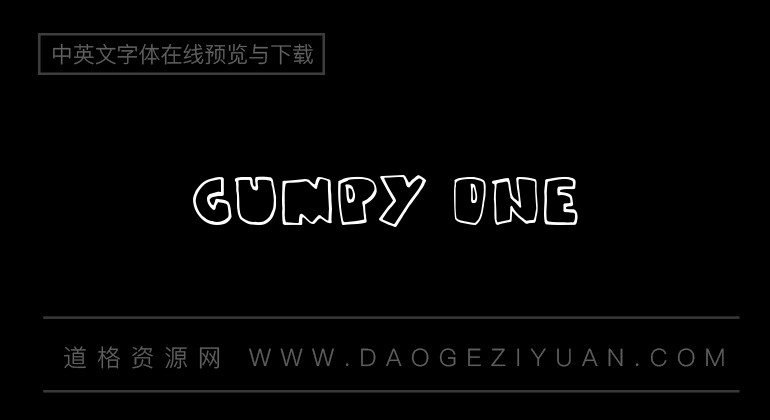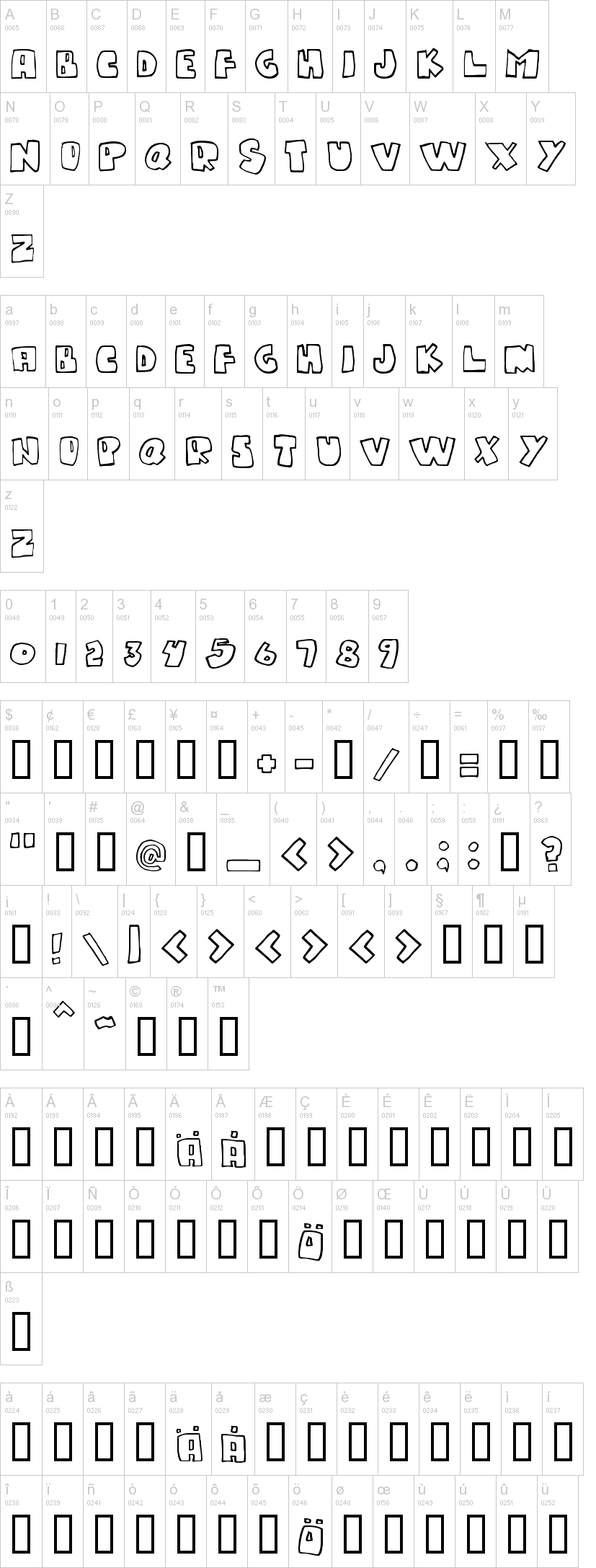
Gumpy One 是一款拥有独特风格的字体,由著名的设计师 Gumpymeme 创作。这款字体融合了多种元素,包括古典、现代、抢眼的显示效果等。它的字形混合了单词和字母,营造出一种轻松愉快的氛围。Gumpy One 字体有着清晰的线条,以及一种令人着迷的视觉效果,可以用于多种用途,比如平面设计、头像、印刷品、海报、标识等等。内容介绍
Gumpy One是一款非常不错的手写艺术字体,具有很好的视觉感,适合于文化类的宣传设计、商业类品牌的广告和产品包装设计以及个性化文字排版等较多场景。